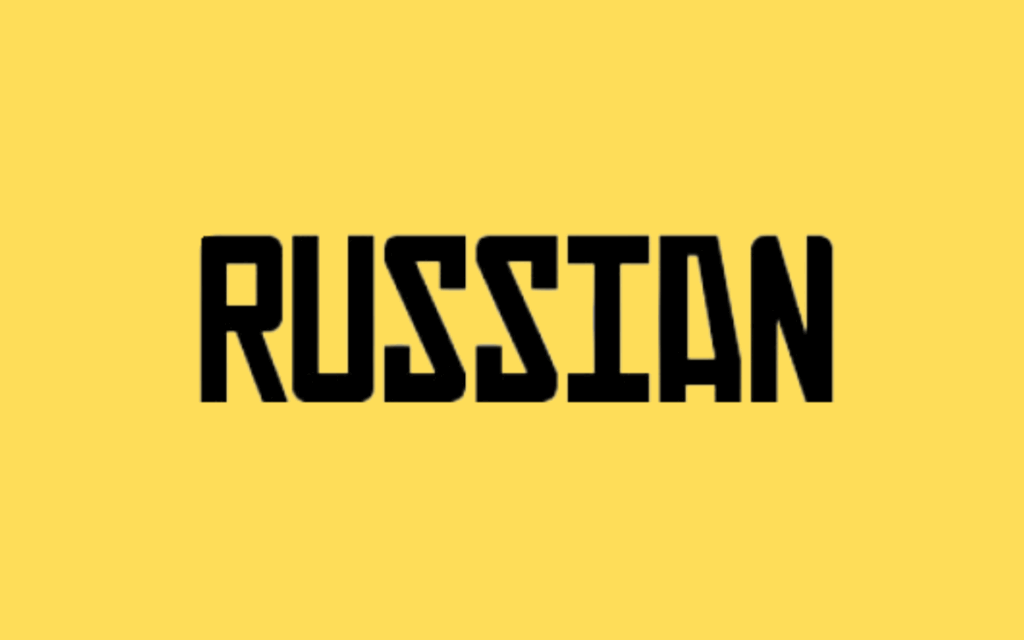
Tải font tiếng Nga full là nhu cầu thiết yếu đối với các kiến trúc sư, nhà thiết kế và đơn vị thi công khi triển khai các dự án phục vụ du khách quốc tế hoặc làm việc với các đối tác liên doanh dầu khí, công nghiệp nặng. Hệ chữ cái Kirin với các con chữ đặc thù như ‘Ж’, ‘Д’, ‘Ф’, ‘Я’ đòi hỏi phông chữ phải hỗ trợ bảng mã chuẩn để không gặp sự cố lỗi ký tự trên bản vẽ kỹ thuật hay biển hiệu thực tế.
Hệ chữ cái Cyrillic đĩnh đạc và khả năng tương thích đa ngữ của bộ font tiếng Nga full
Điểm giá trị của bộ tài nguyên khi bạn tải font tiếng Nga full nằm ở sự tích hợp hoàn thiện giữa hệ chữ cái Latinh mở rộng (có đầy đủ dấu thanh tiếng Việt) và 33 ký tự chữ cái tiếng Nga bản địa. Cấu trúc chữ Cyrillic sở hữu nét thẳng vững chãi, các đường nối hình học khỏe khoắn mang lại cảm giác kiên cố, chuẩn mực như phong cách kiến trúc Xô Viết kinh điển.
Sự ổn định về mặt thị giác của dòng font này giúp nâng cao tính thân thiện và trải nghiệm dịch vụ cho du khách quốc tế. Khi xuất hiện trên các bề mặt vật liệu kiến trúc ven biển như tấm alu ngoài trời, biển gỗ thông khắc chìm hay vách kính dán decal chỉ dẫn tại các khu homestay nghỉ dưỡng, tiếng Nga mang lại sự an tâm và thuận tiện cho khách lưu trú.
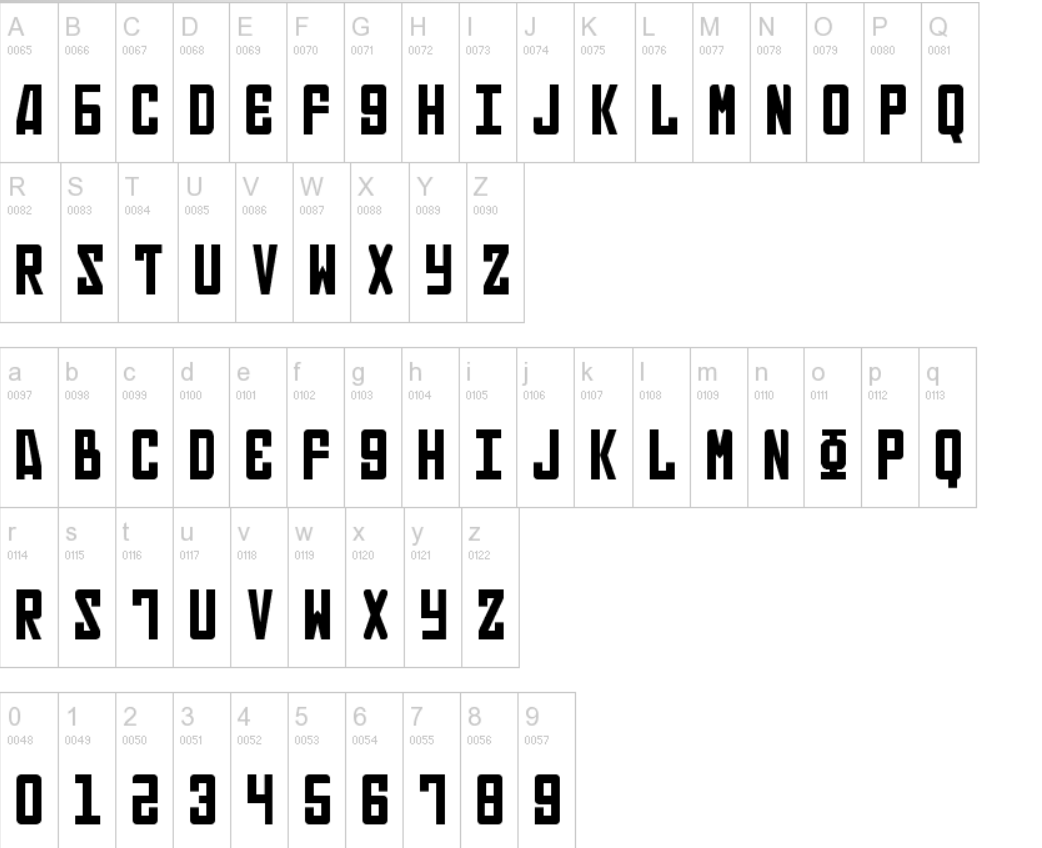
Tư vấn từ chuyên viên: Khi thiết kế biển hiệu song ngữ, bạn nên chọn các bộ phông chữ thuộc cùng một gia đình để phần chữ tiếng Việt và tiếng Nga có độ dày nét và chiều cao tương đồng. Điều này giúp bố cục biển báo đạt tính thẩm mỹ cân đối và không gây cảm giác lộn xộn cho người đọc.
03 Ứng dụng Font chữ tiếng Nga đẹp vào công trình thực tế
Nhờ tính chuẩn mực và khả năng nhận diện cao của bảng mã Cyrillic, bộ phông chữ này mang lại giá trị thực tế lớn trong khâu vận hành các mô hình du lịch và công nghiệp:
- Hệ thống biển chỉ dẫn lối đi tại Khu nghỉ dưỡng Ven biển: Sử dụng Font chữ tiếng Nga đẹp cho biển tên bãi tắm, quầy dịch vụ hoặc hướng dẫn an toàn giúp du khách Nga cảm nhận được sự chu đáo và thân thiện của khu homestay lắp ghép.
- Bảng thực đơn và Bảng giá dịch vụ du lịch: Phông chữ này khi in trên giấy kraft hoặc bảng mica treo tường sẽ giúp các món ăn, dịch vụ tour hiển thị rõ ràng, giúp quá trình giao tiếp giữa nhân viên phục vụ và du khách diễn ra thuận lợi.
- Bản vẽ kỹ thuật và Hồ sơ dự án liên doanh: Ứng dụng phông chữ tiếng Nga chuẩn trên phần mềm AutoCAD giúp các kỹ sư Việt Nam và chuyên gia Nga dễ dàng phối hợp bóc tách khối lượng và giám sát thi công kết cấu nhà lắp ghép công nghiệp.
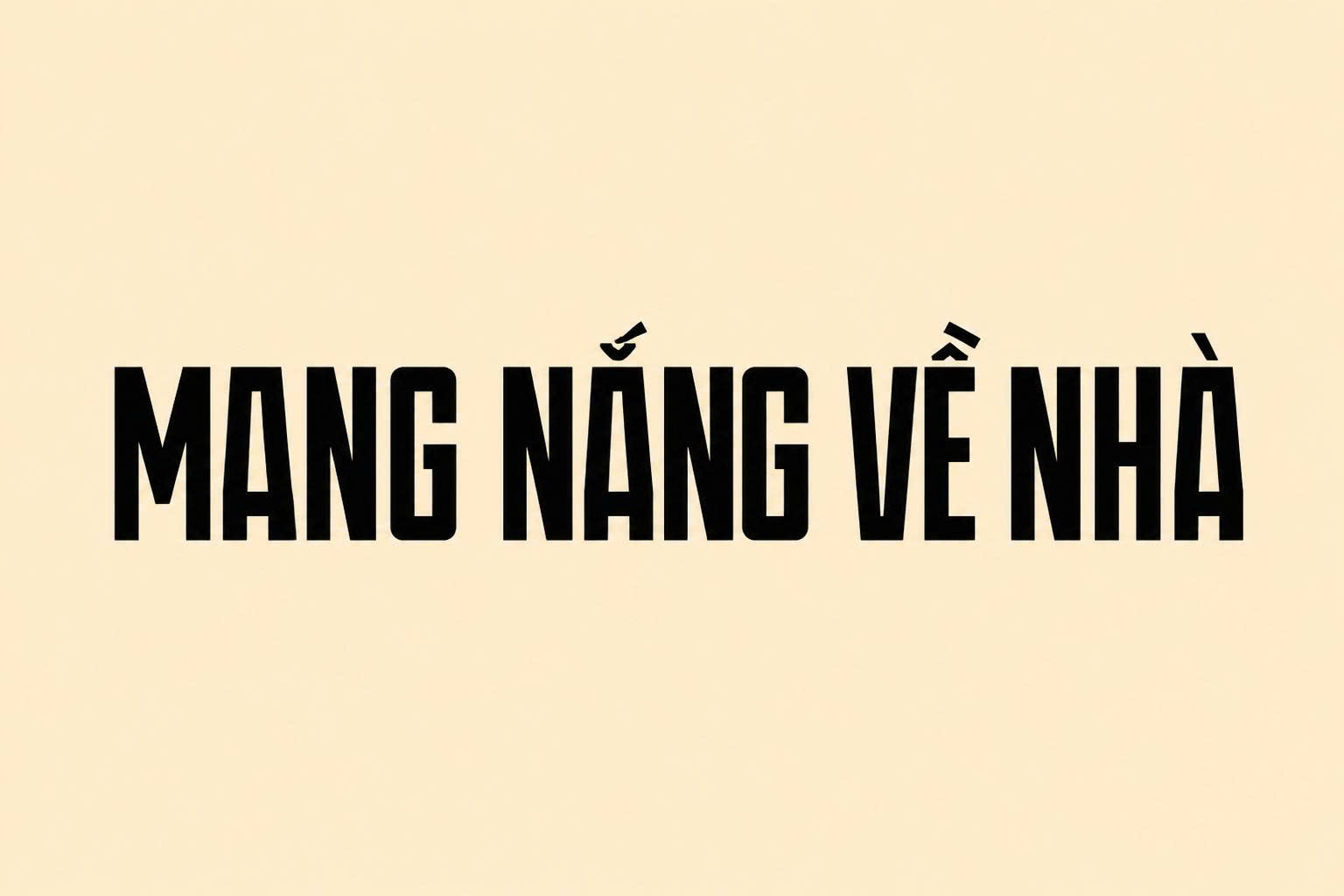
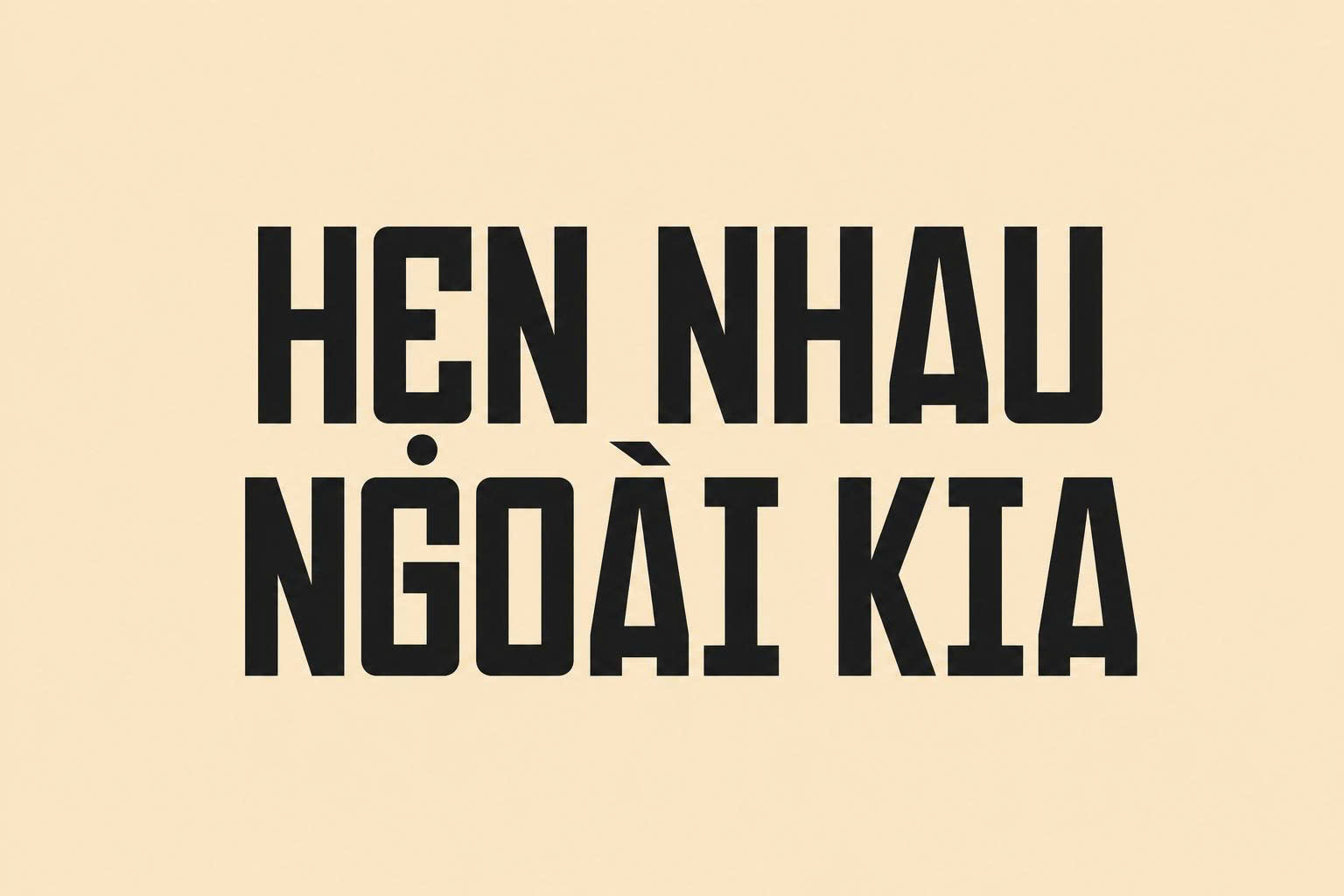
03 Lưu ý bố cục phông chữ tiếng Nga luôn mạch lạc và chuẩn quy ước
Để khai thác hiệu quả vẻ đẹp của dòng font chữ Cyrillic này mà không làm rối mắt người xem, người thiết kế nên lưu tâm một số kinh nghiệm sau:
- Lưu ý sự khác biệt giữa chữ in và chữ viết tay tiếng Nga: Một số ký tự tiếng Nga có hình dạng viết tay (Italic) khác biệt hoàn toàn so với kiểu đứng (như chữ ‘т’ thành ‘m’, chữ ‘д’ thành ‘g’). Bạn nên cân nhắc ngữ cảnh kỹ thuật hay nghệ thuật để chọn kiểu đứng hoặc nghiêng cho phù hợp.
- Kiểm soát khoảng cách dòng: Do một số con chữ Cyrillic có đuôi móc vươn xuống dưới khá dài, bạn nên thiết lập khoảng cách dòng thoáng đãng (khoảng 1.4 lần cỡ chữ) để các dòng chữ không bị chạm nhau.
- Đồng bộ thứ tự ngôn ngữ trên biển báo: Quy ước chuẩn là đặt tiếng Việt ở vị trí trên cùng hoặc kích thước lớn hơn, tiếp theo là tiếng Anh và tiếng Nga bên dưới để đảm bảo tính mỹ quan và thứ tự ưu tiên của văn bản hành chính.